Jak podpisywać obrazy czcionką Game of Thrones na iOS
Serial "Gra o tron" z pewnością zapisał się w historii jako jeden z najbardziej rozpoznawalnych programów telewizyjnych, a także jako jeden z najczęściej pirackich. Oferuje niezwykłe postacie oraz znakomite one-linery, które doskonale nadają się jako podpisy do zdjęć. Nie chodzi jednak tylko o dialogi; czcionka używana w tym serialu stała się równie popularna, jak te z serii "Harry Potter" czy "Władca Pierścieni". Jeśli chcesz dodać podpisy w stylu "Gry o tron" do swoich zdjęć na iPhonie, możesz skorzystać z aplikacji o nazwie Game of Fonts.
Czcionka z Gry o Tron
Game of Fonts to darmowa aplikacja, którą możesz ściągnąć z App Store. Po jej uruchomieniu, przyciski na dole ekranu pozwolą na wybór zdjęcia lub wideo, do którego chcesz dodać podpis oraz ramkę.
Najpierw załaduj wideo lub zdjęcie, a następnie wybierz czcionkę (pierwszy przycisk od lewej) lub ramkę (trzeci przycisk od lewej).
Aplikacja oferuje odpowiednią czcionkę oraz ramki charakterystyczne dla serialu, choć obie te funkcje mają swoje ograniczenia. Można zmieniać rozmiar czcionki, jednak najmniejsza dostępna wielkość nadal pozostaje dość duża. W aplikacji znajdują się trzy rodzaje ramek: rama Żelaznego Tronu, rama Ognia oraz rama Lodu. Czcionka występuje w tych samych wariantach, a oprócz rozmiaru można dostosować również wyrównanie tekstu.
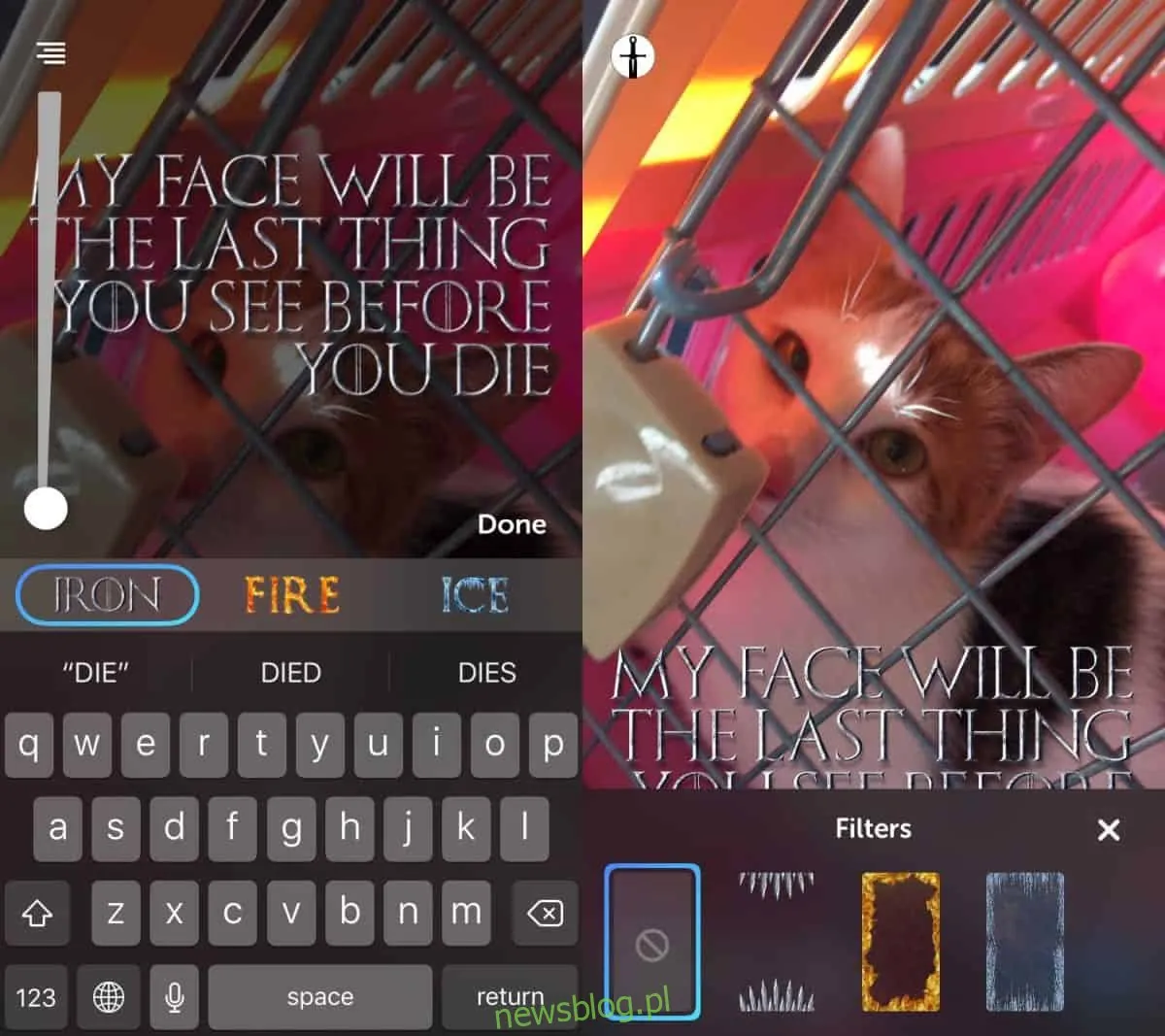
Po dodaniu podpisu do obrazu możesz go zapisać w galerii zdjęć lub udostępnić na różnych platformach społecznościowych. Co istotne, obraz nie zawiera znaku wodnego ani żadnych innych oznaczeń.
Prawdziwym wyzwaniem jest stworzenie atrakcyjnego obrazu i jego skuteczne udostępnienie w mediach społecznościowych. Czcionki nie zawsze są dobrze widoczne na różnych typach zdjęć. Jeśli korzystasz z ciemniejszego tła, lepiej zastosować czcionkę i ramkę Żelaznego Tronu lub Lodu. W przypadku jaśniejszego tła, wersja Ognia może być najłatwiejsza do odczytania. Jeśli chcesz połączyć czcionkę tej aplikacji z innymi platformami społecznościowymi, najpierw utwórz obraz w danej aplikacji, a następnie zapisz go w rolce aparatu. Następnie możesz załadować go do aplikacji Game of Fonts i dodać podpis.